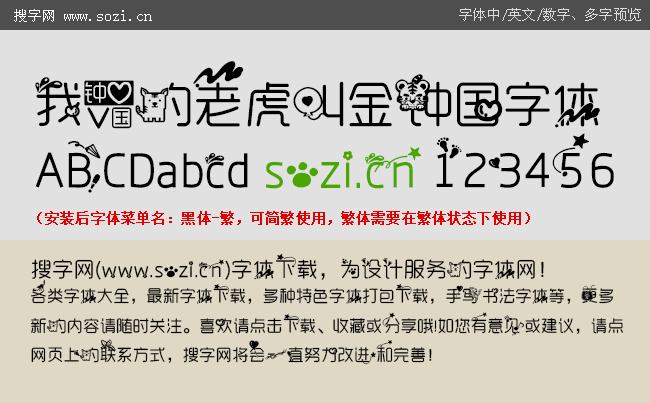
我愛的老虎叫金鐘國字體
搜字網(wǎng)給大家提供一款很有趣的手機(jī)中文字體下載。修改者給他起名為叫我愛的老虎叫金鐘國字體,這款手機(jī)字體是在造字工房悅黑體字體筆畫間插入了可愛老虎等卡通圖案。趣味性實足,又保持了文字的識別度,特別適合喜歡手機(jī)字體個性一些的朋友在手機(jī)上安裝使用。